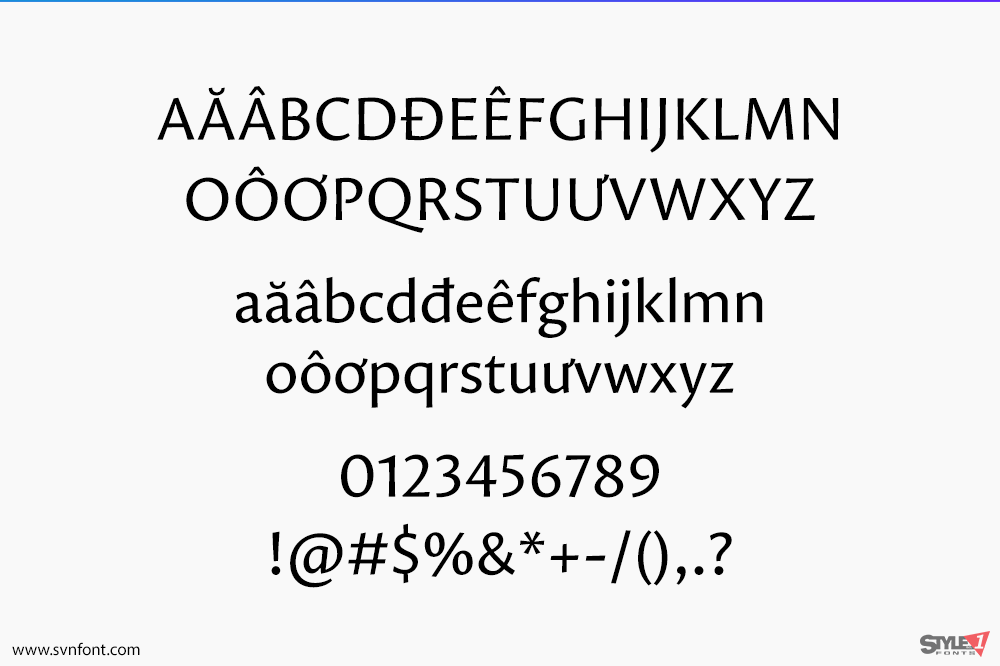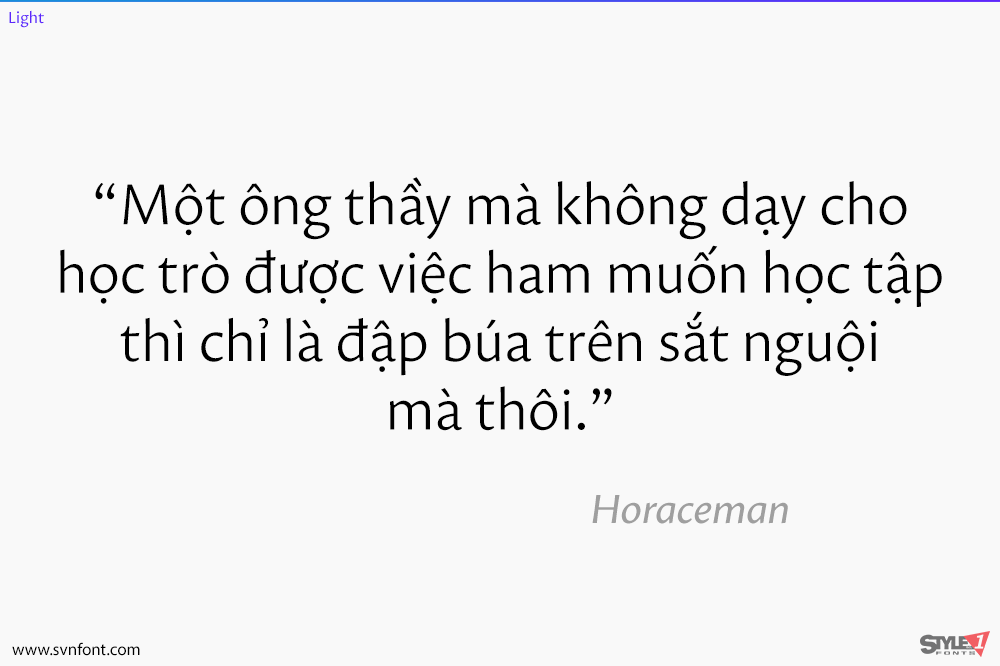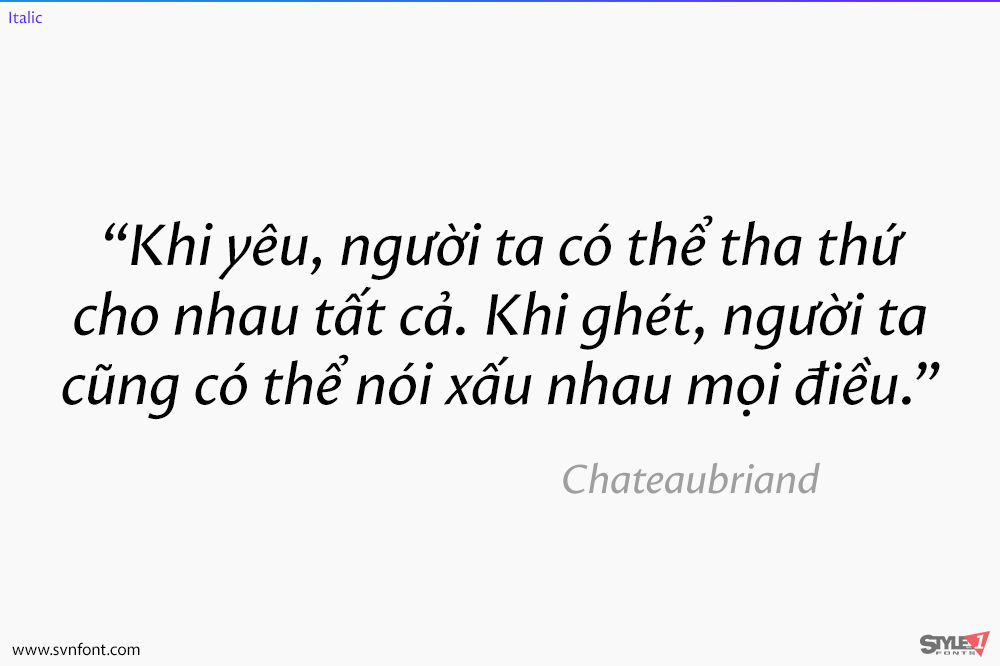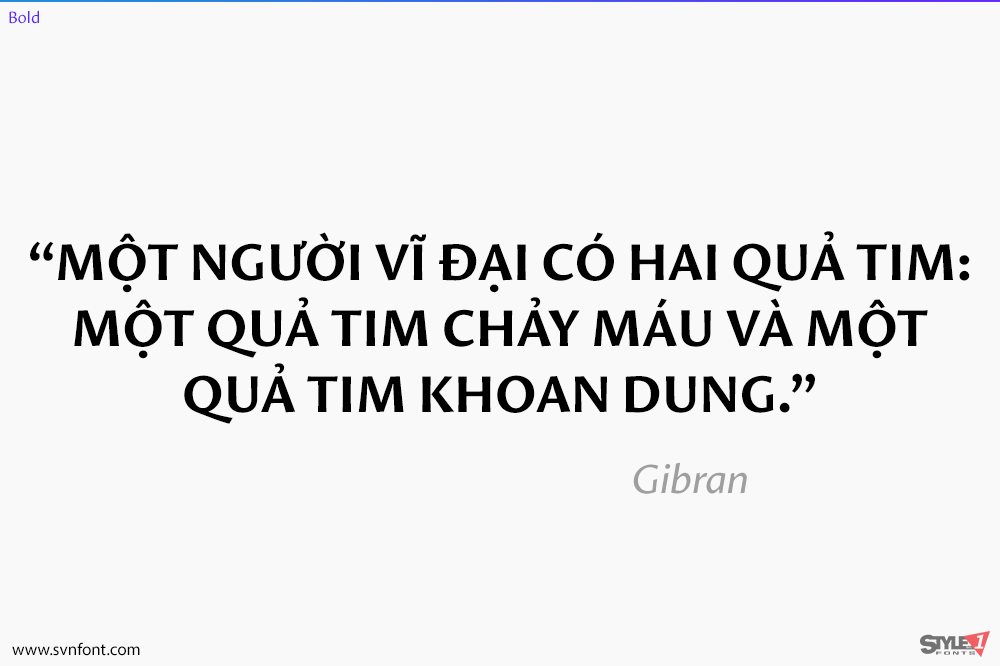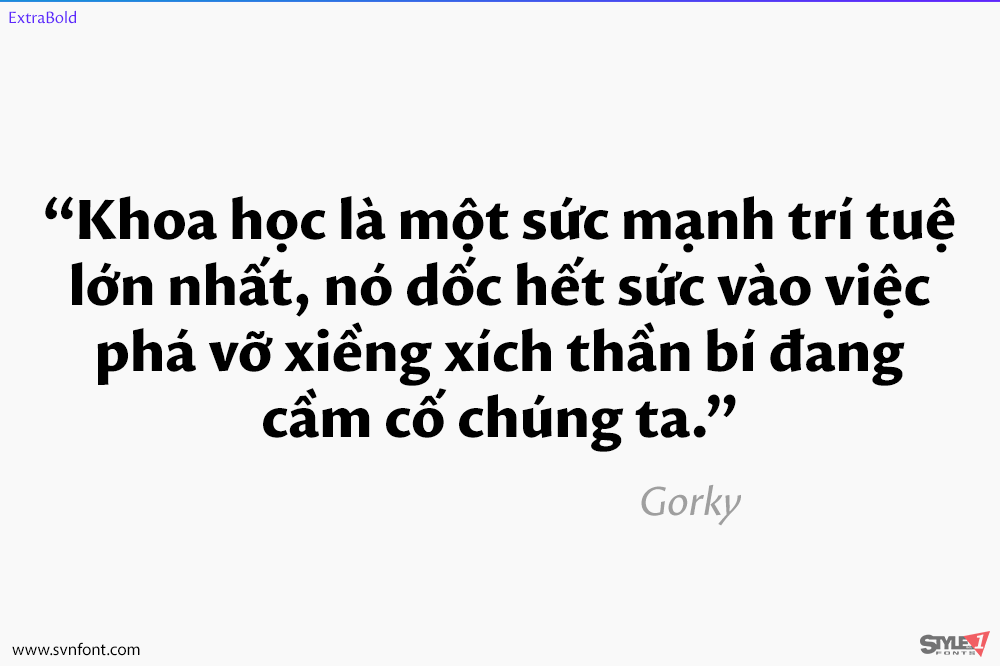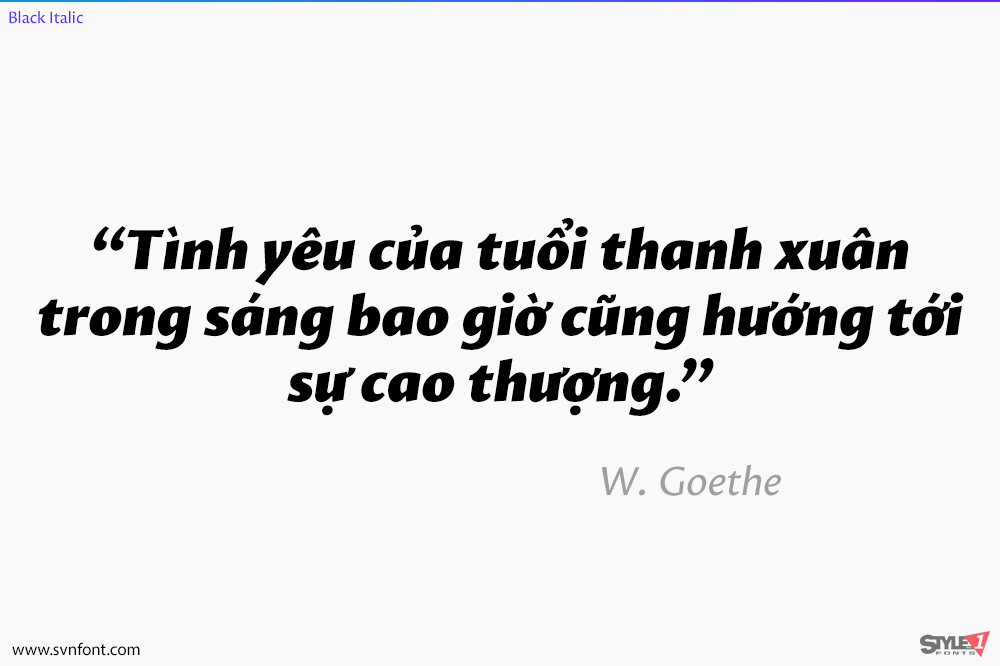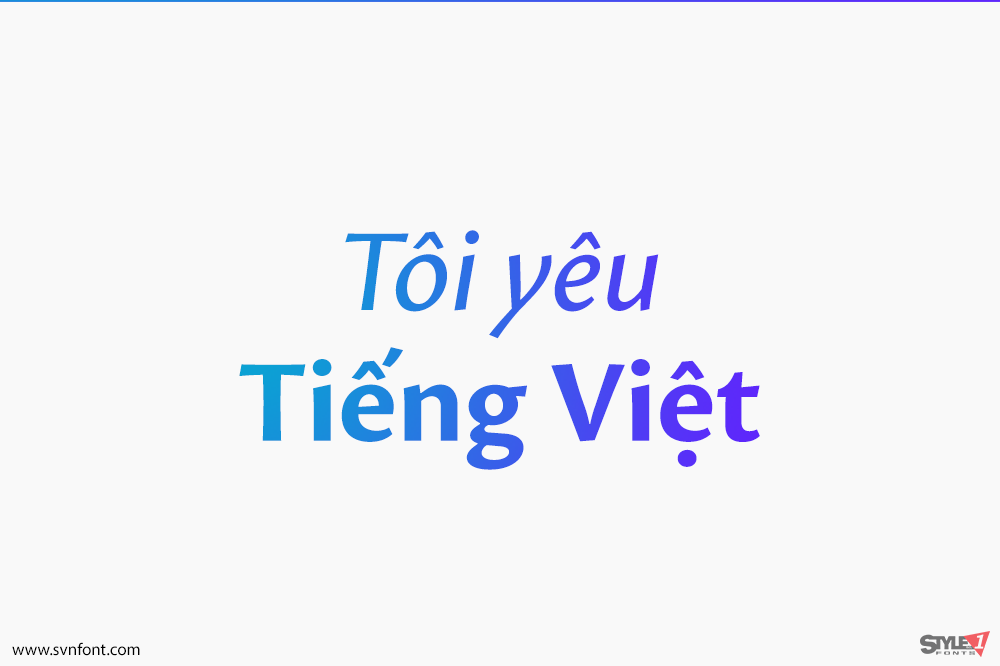
Proza là một bộ phông chữ sans serif theo phong cách nhân văn, bao gồm 12 kiểu (6 độ đậm + chữ nghiêng), với nguồn gốc từ các thiết kế serif thời Phục hưng, chẳng hạn như Garamond và Jenson. Proza được tạo ra để hoạt động tốt ở nhiều kích cỡ, từ kích thước văn bản nhỏ nhất đến các poster khổng lồ, làm cho nó trở thành một bộ phông chữ cực kỳ linh hoạt. Bộ ký tự lớn (hỗ trợ hơn 100 ngôn ngữ) và các tính năng opentype của nó sẽ giúp bạn giải quyết mọi vấn đề, trong khi sự thanh lịch và các chi tiết tinh tế của nó đảm bảo mang lại một “cú đấm” đẳng cấp cho các thiết kế của bạn. Một bài viết chi tiết về sự phát triển và thiết kế của Proza có trên trang ilovetypography.com.
Nhà thiết kế: Jasper de Waard